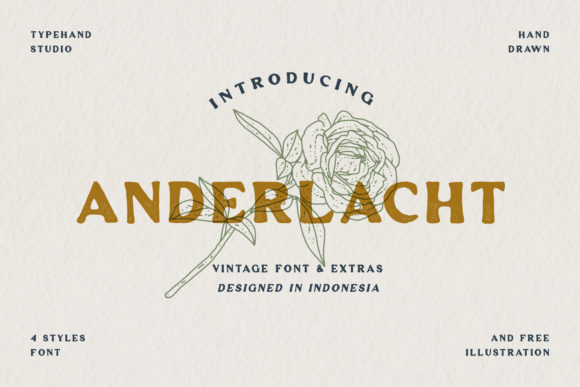
Название: Anderlacht Font (2021)
Anderlacht - это крутой дисплей с толстыми буквами в винтажном стиле. Его можно легко сопоставить с невероятно большим набором проектов, поэтому добавьте его к своим творческим идеям и обратите внимание, как они выделяются среди них!
Название: Anderlacht Font (2021)
Anderlacht - это крутой дисплей с толстыми буквами в винтажном стиле. Его можно легко сопоставить с невероятно большим набором проектов, поэтому добавьте его к своим творческим идеям и обратите внимание, как они выделяются среди них!